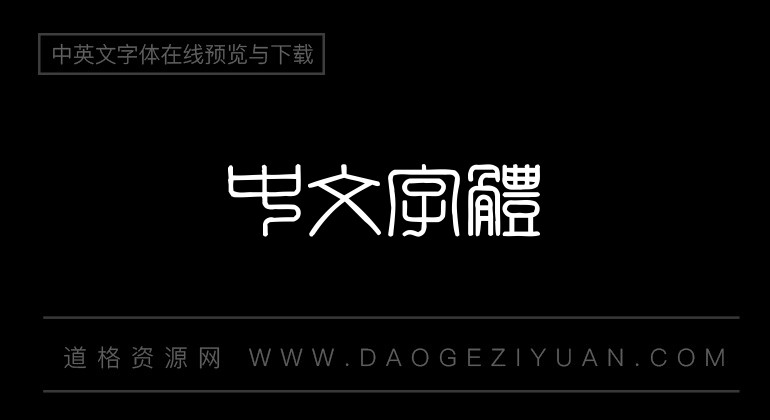
汉鼎繁印篆
汉鼎繁印篆字体是一种古老的中国字体,发源于魏晋时期,晚至唐宋时期发展壮大,是中国传统文化的重要组成部分。它的特点是字体细腻,笔画精练,笔法精致,构图严谨,极富古典气息,有着浓厚的中国文化底蕴。汉鼎繁印篆字体在历史上曾经得到广泛的使用,比如在皇家宫殿、宗教场所、书法市场等地方,都有它的身影。
汉鼎繁印篆是一款非常不错的手写艺术字体,具有很好的视觉感,适合于文化类的宣传设计、商业类品牌的广告和产品包装设计以及个性化文字排版等较多场景。